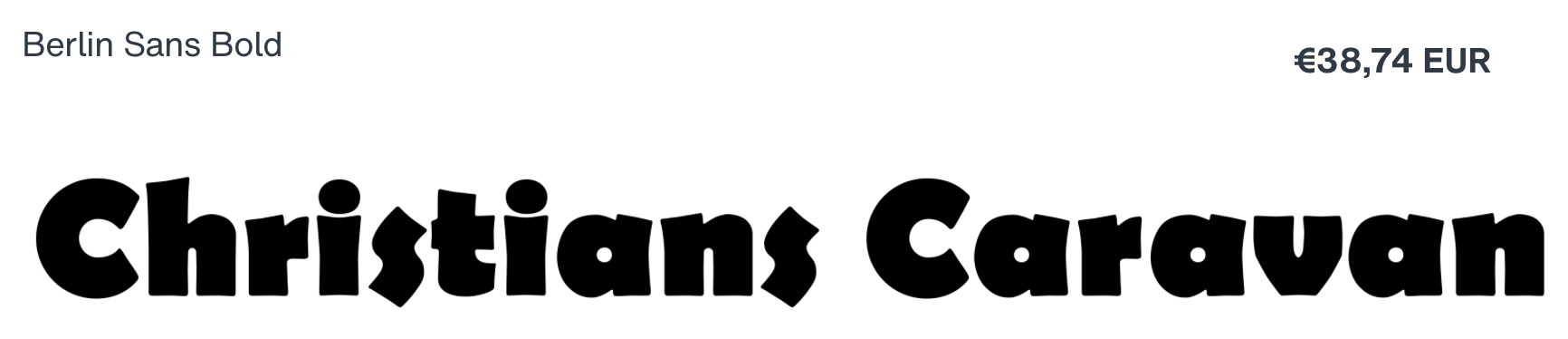
Typo für Logo-Relaunch dringend gesucht
ich darf ein Logo überarbeiten, finde aber die Schrift dazu nicht. Das Logo wurde bisher nur auf der Homepage für eine Firma verwendet , die Wohnmobile verleiht und verkauft. IN meinem Muster sieht in der Vergrößerung die Typo recht "krackelig" aus, soll aber "kantenscharf" sein. Das Logo soll später auf einem Fahrzeug in größerer Form erscheinen.
Bei einem Relaunch des Logos würde ich empfehlen auch die Schrift zu überdenken. Für mich passt sie nicht so recht zum Geschäftsfeld ... ich würde eine klarere bzw. stabilere Schrift empfehlen.
… absolut. Aber es ist ein neuer Kunde, den ich noch nicht so gut kenne. Eine neue Typolösung tut hier unbedingt Not!